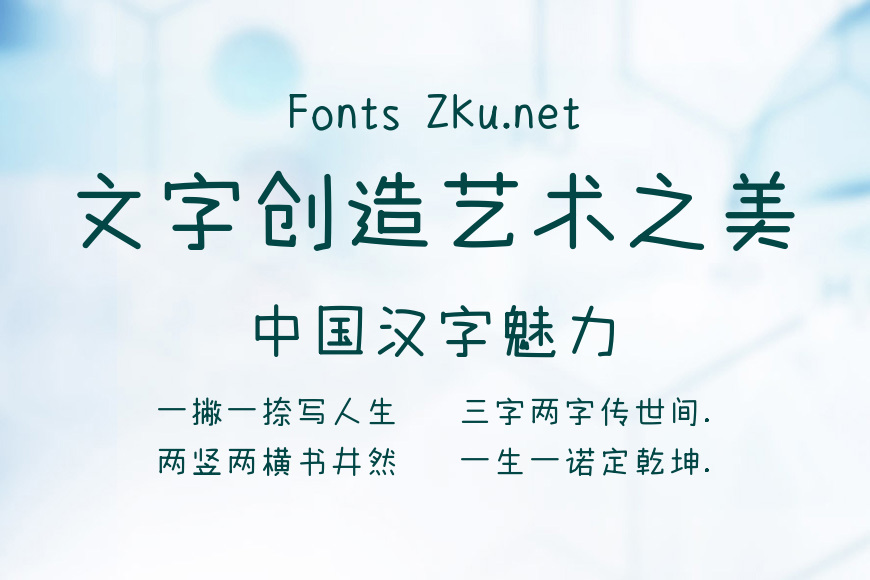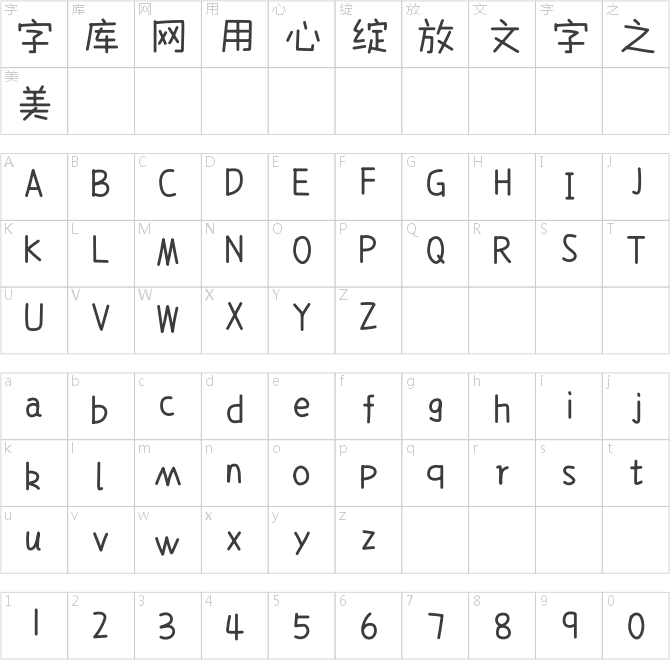
字帮玩酷体
字帮玩酷体介绍
2022年,我们将精力始终如一的放在这款字体上,无论是质量还是数量,我们团队都非常有信心它可以带给大家更有趣、更丰富的使用感受。
我们将这套字体取名“字帮玩酷体”,像名字一样,它的字形风趣,笔画多元,字形错落有致,风格轻松玩趣,收录GBK编码共20923个文字及987个符号,满足各种使用场景。相信大家在打一些生僻字时会有“被默认”的情况,字体很难统一,但字帮玩酷体无论是常用字还是生僻字都不会让大家有这样的烦恼。